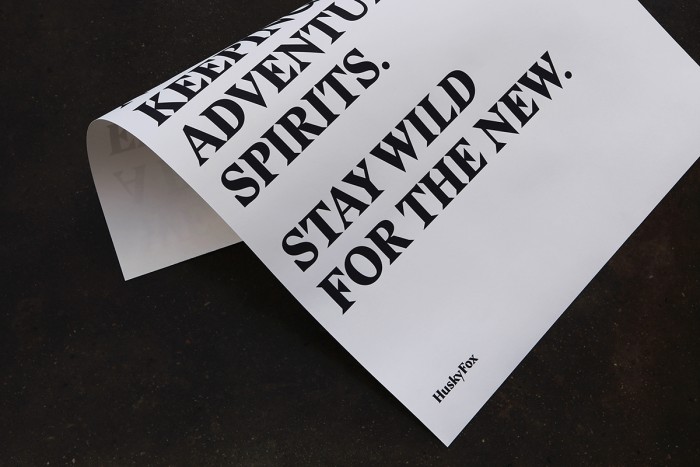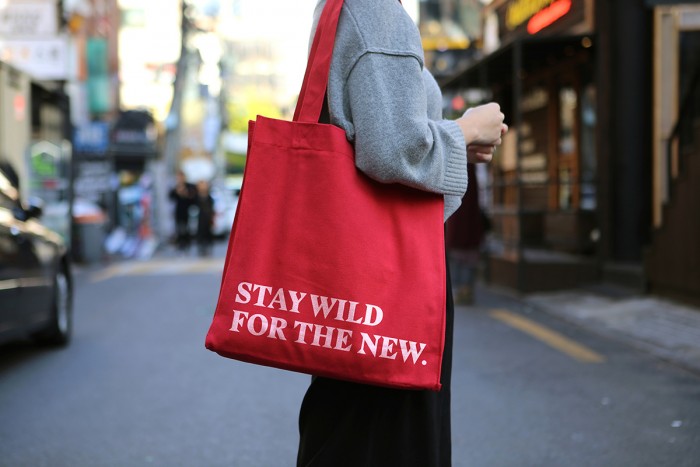
Suche den Namen dieser Schriftart (Serifenbetont, Wedge Serifs)
Ich bin auf der Suche nach dieser Schriftart. Die Serifen haben keine Kehlung, sondern sehr "keilige" Übergänge.Die üblichen "Whatthefont..." etc. brachten kein Ergebnis.
Nachdem HuskyFox eine Brand-Agentur ist, liegt die Vermutung nahe dass sie nicht irgendeinen verfügbaren Font genommen haben …
Ich meine ich hätte diesen Typeface schon irgendwann vor der Nase gehabt. Ich weiss einfach nicht aus welchen Haus der ist. Ich glaube nicht, dass sie eine neue extra gebaut haben. Im Logo vielleicht, aber beim Schriftsatz nicht. glaube ich eher nicht.
Mir kommt sie auch bekannt vor, kann aber erstmal nur mit ähnlichen Fonts dienen:
Yeah, vielen Dank! Die Noe Display geht in die Richtung. Gibt es einen Namen für diese Serifenform. Das frag ich mich nämlich schon lange...
Ich meine auch, dass wir diese oder so eine kürzlich (?) schon gesucht haben …
Ah, danke für den Schlag auf den Hinterkopf! Jener thread war’s, in dem die Stanley gesucht wurde. Das hatte ich irgendwie im Hinterkopf :-)